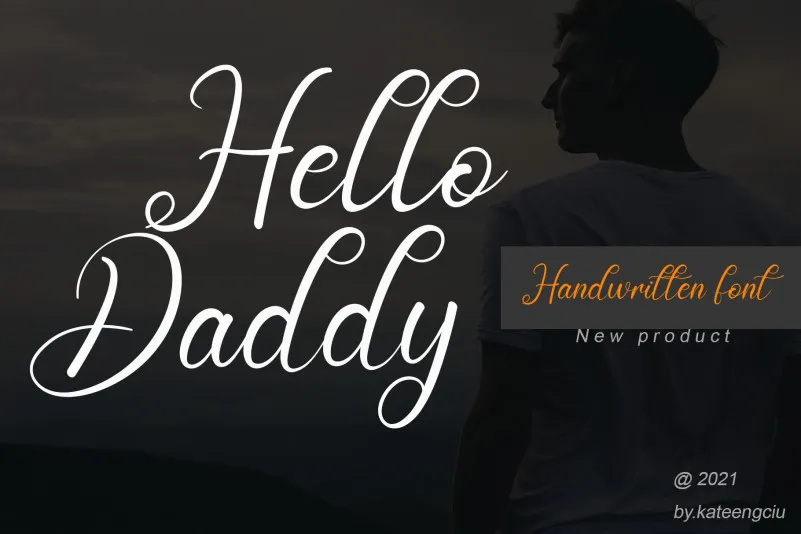
Hello Daddy Font – Fonte Grátis
Hello Daddy Font
Esta é uma fonte de escrita manuscrita elegante com um clima contemporâneo e forma perfeita, inspirada em alfabetos clássicos que nunca saem de moda. Ela transmite uma atmosfera aconchegante e natural, ideal para projetos que buscam adicionar um toque delicado e sofisticado à sua criação. Não é fina demais nem grossa demais; mantém-se harmoniosa e diversificada, proporcionando o equilíbrio perfeito em cada caractere. A fonte foi criada para destacar a beleza do seu trabalho. Seja você um designer de arte digital ou uma pessoa que simplesmente adora criar belas imagens digitais, ‘Hello Daddy Font’ é uma escolha excepcional.